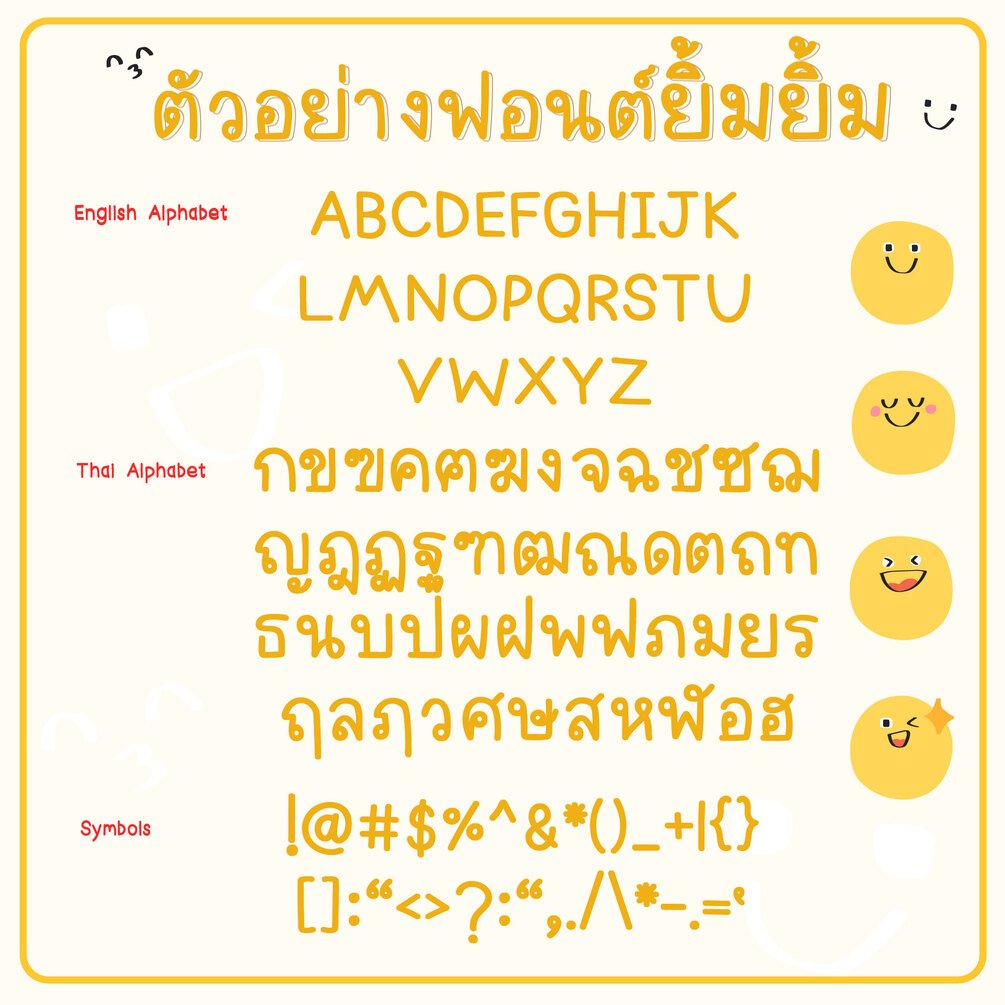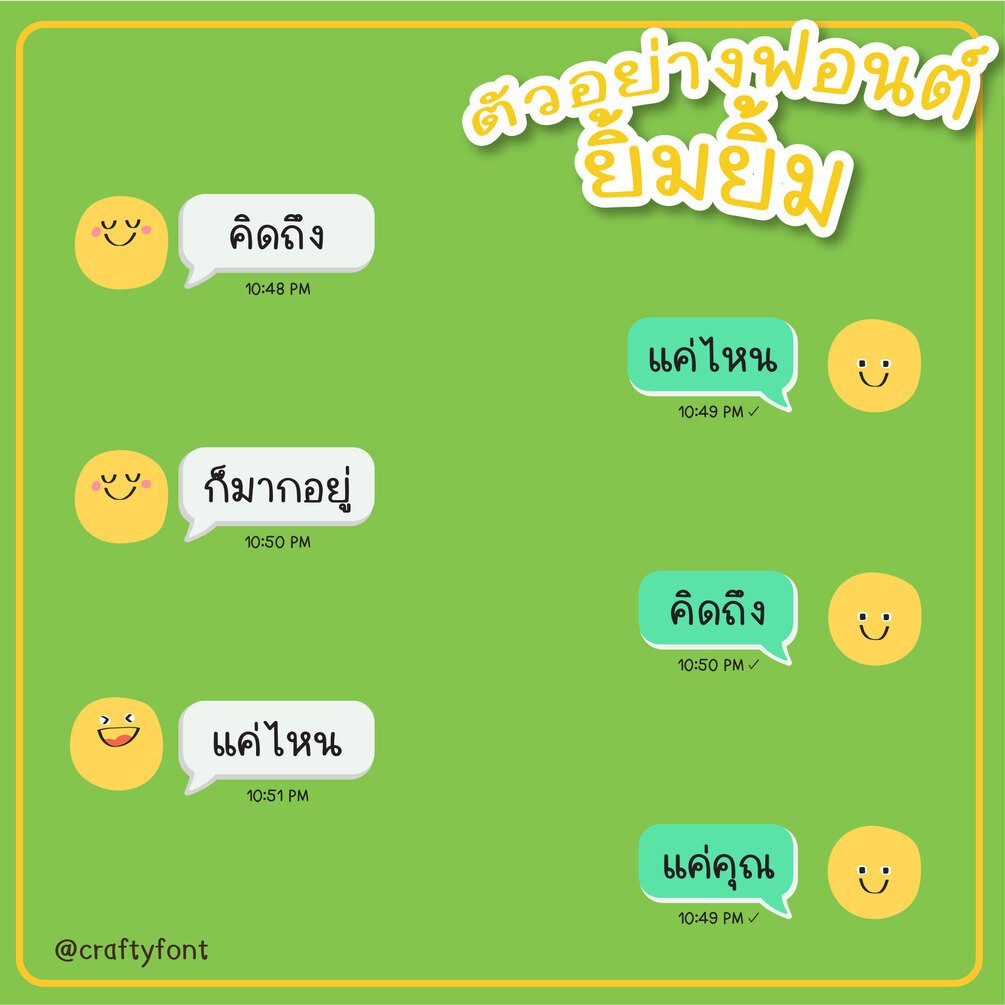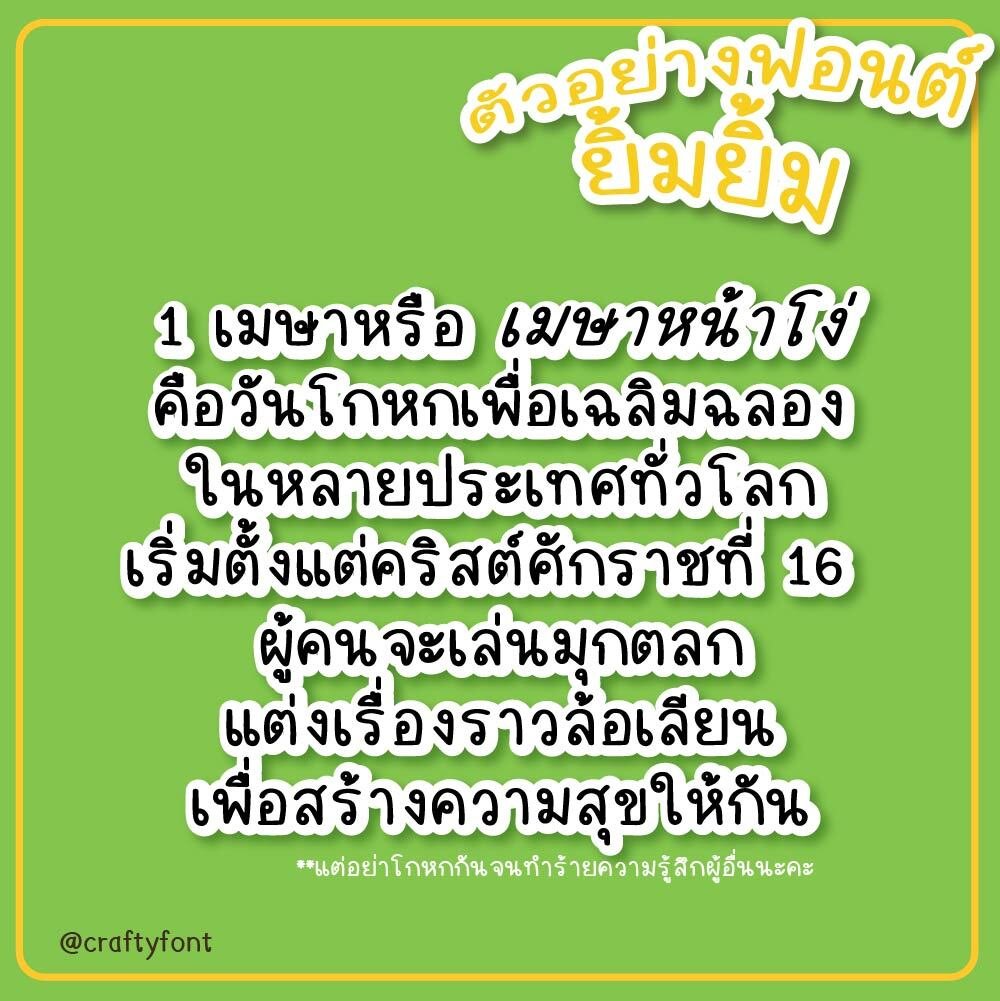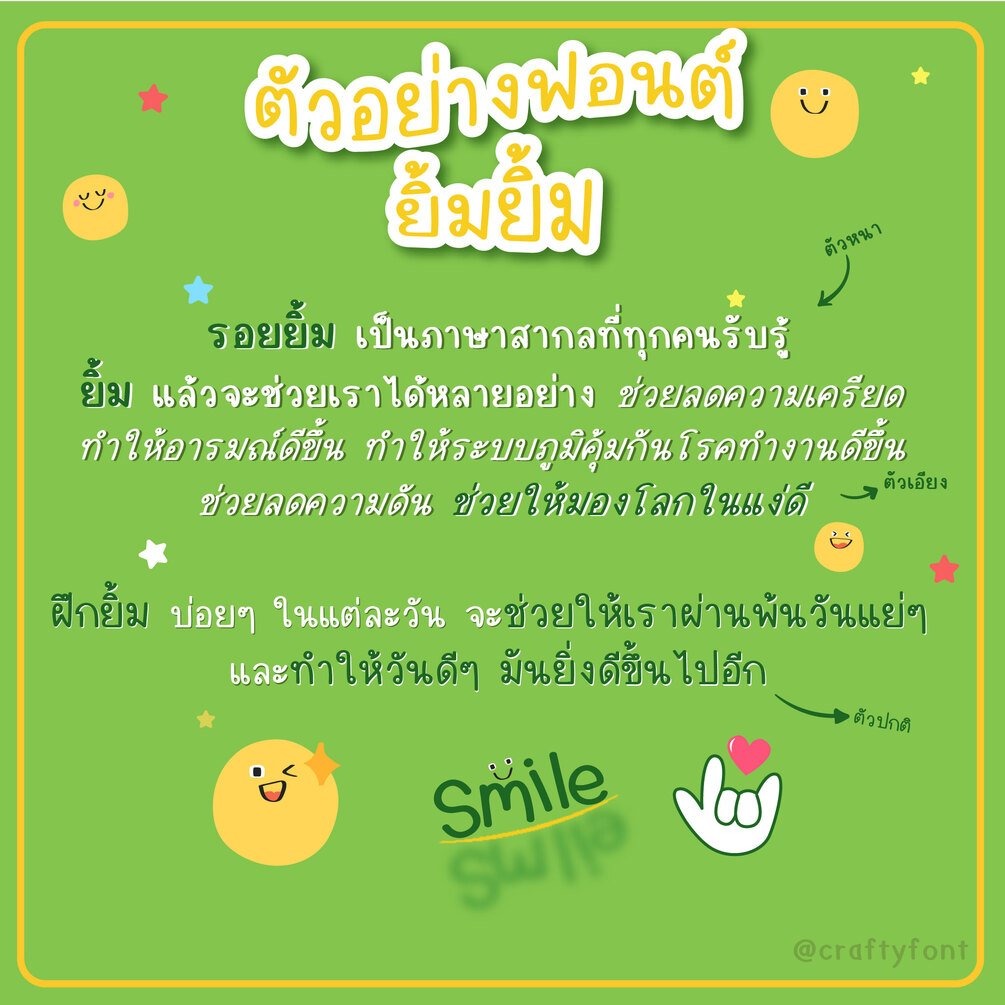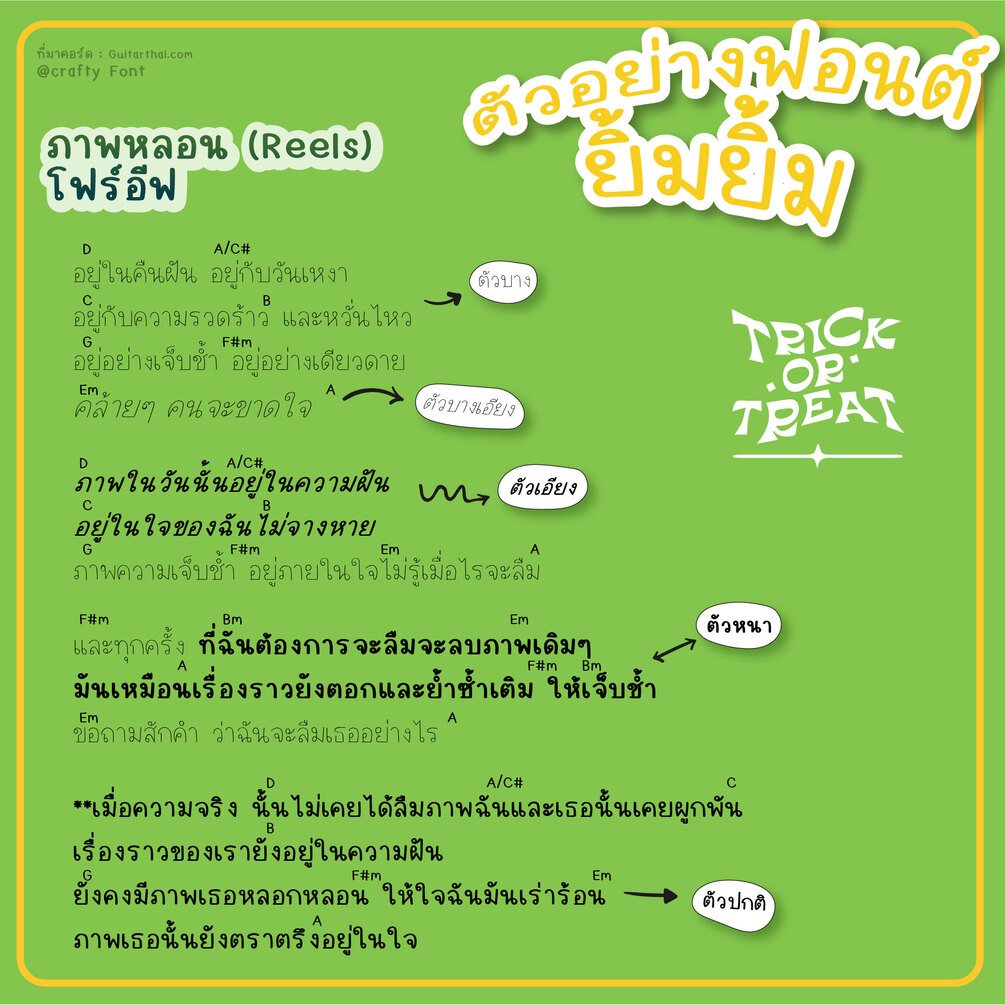
Smile Font (ฟอนต์ยิ้มยิ้ม)
ใครบอก crafty font ชอบเขียนฟอนต์ตัวใหญ่ๆ หนาๆ ต้องฟอนต์ยิ้มยิ้มเลยฮะ! ฟอนต์ตัวบาง จะบางประหนึ่งเขียนด้วยดินสอ เกร็งมือมากเลยตอนเขียน ไม่เคยเขียนด้วยบรัชบางขนาดนี้ +O+
เหมาะกับนักเรียนเอาไว้โน้ต แล้วเน้นด้วยตัวปกติ หรือตัวหนา จะให้ความรู้สึกตัวเน้นมันพุ่งใส่หน้าเลยค่ะ!
ฟอนต์มีทั้งภาษาไทยและภาษาอังกฤษเลยนะคะ บวกลบคูณหารมีให้ใช้ครบ ฝากไว้ในอ้อมอกอ้อมใจพี่จ๋าด้วยนะจ๊ะ
แฟมิลี่ชุดนี้มีถึง 5 แบบด้วยกัน! ตัวปกติ ตัวหนา ตัวบาง ตัวเอียง และตัวบางเอียง!